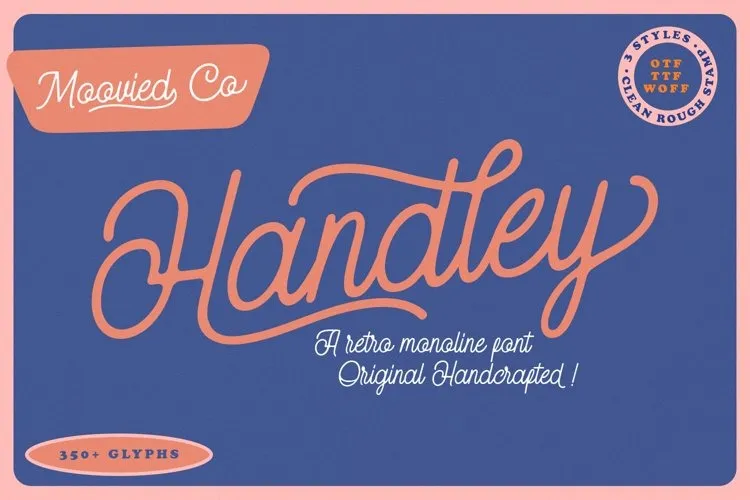
Handley Font – Fonte Grátis
Handley Font
A Handley Font é uma elegante escolha para designers gráficos que buscam um estilo vintage e sofisticado. Fabricada pela TempCraft, esta fonte monoline vem inspirada no design de sinais e selos dinâmicos, oferecendo aos criativos uma opção versátil para criações como logotipos, cartões de convite, embalagens, selos e roupas. Com um ar retro que transmite modernidade e elegância, a Handley Monoline Display é perfeita para projetos que exigem um tom vintage sofisticado. Além disso, Arkland, outra criação da TempCraft, reflete o mesmo estilo dinâmico e retro, com uma visão mais contemporânea, tornando-a ainda mais versátil para um leque amplo de aplicativos. Essa fonte é perfeita para quem busca criar identidades visuais memoráveis que se destacam no mercado atual, ao oferecer tanto uma conexão nostálgica quanto a frescura do design moderno.